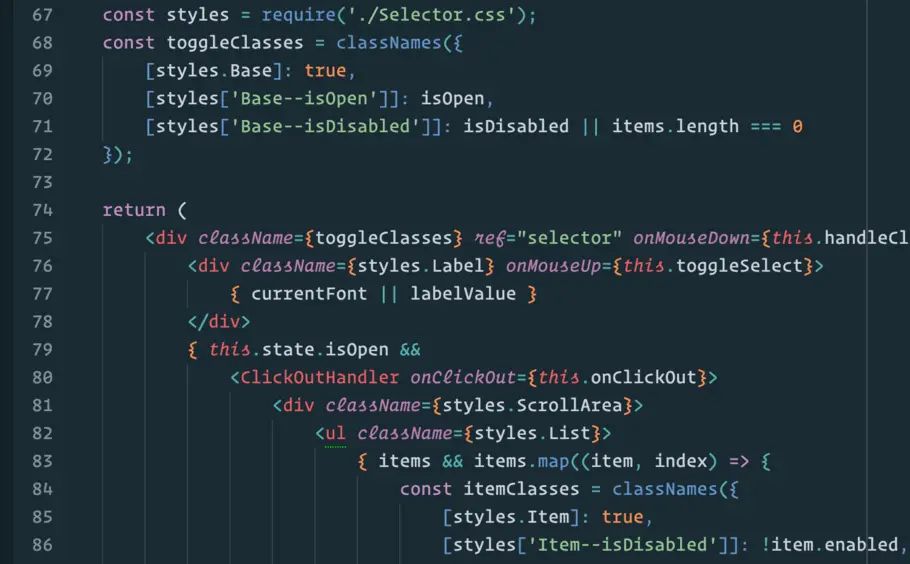
An extended family of typefaces shaped by a common writing tool, Inkwell’s many voices are designed to give rise to new kinds of typographic relationships.
Operator 模拟打字机字体的功能与风格,包含两个字体家族:一个适合图文编辑,另一个适用于计算机代码编辑。
灵感源于手表表盘,Decimal 字体唤起了人们对经典钟表刻度文字的记忆。此外,Decimal 还融入了诸多设计巧思,让字体适应信息密集的环境。
字体设计师 Jordan Bell 着迷于手写字体,深入研究其对于现代字体设计和美国字体基础的影响。Jordan 的家乡位于美国德州,他在阿比林基督教大学获得学士学位。在加入蒙纳前,Jordan 曾在新墨西哥州圣达菲从事平面设计。
加入蒙纳前,Jordan 在 Hoefler&Co. 参与各类字体项目,包括 Operator、Inkwell 和 Decimal 字体。这些字体出现在 Netflix 纪录片《Abstract》中,并在拜登总统的竞选活动中使用。其他参与的项目还包括 Archer、Ringside 和 Sentinel Pro。